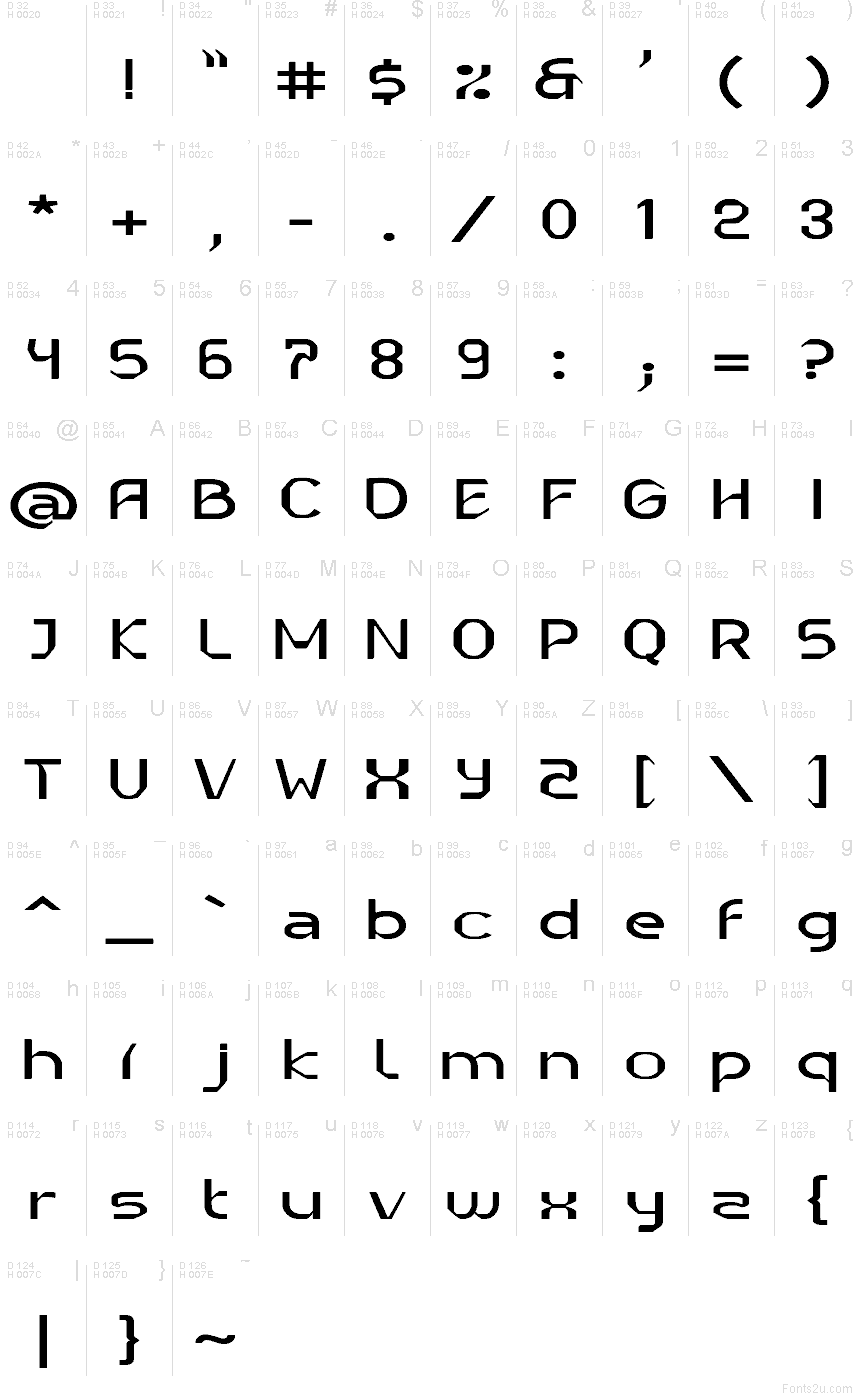
Braven od Solvstud to nowoczesny, darmowy krój typu display o eleganckim, futurystycznym spokoju. Litery łączą szerokie, zaokrąglone łuki z ostrymi, precyzyjnymi łączeniami, tworząc opływowy rytm, który bardziej kojarzy się z konceptualnym brandingiem i technologią niż ze zwykłym bezszeryfowym krojem geometrycznym.
Świetnie odnajduje się w systemach identyfikacji wizualnej, opakowaniach, nagłówkach plakatów, okładkach, czołówkach i krótkich formach brandingowych, gdzie darmowy font potrzebuje bardziej wyrazistego charakteru. Wykorzystaj go do krótkich słów i nazw – niskie, szerokie łuki i nagłe, ostre cięcia nadają nawet prostym napisom świeży, inżynieryjny sznyt, który doskonale sprawdza się w kompaktowych zastosowaniach.